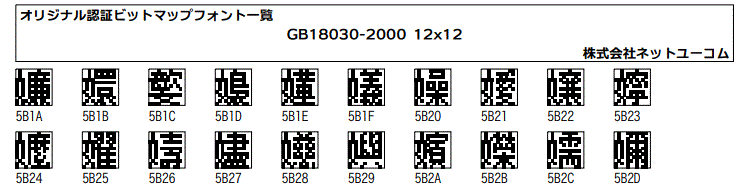
認証フォントをご理解いただいている方には「オリジナル認証フォント」のご提案をさせていただきます。当社保有のGBフォント(中国語ビットマップフォント)は、日本で初めてNIPCの認証を受けたメーカであり、その技術を応用し100%コンパチなGBフォントを制作、民間企業の試験を受けGB規格の中国認証ビットマップフォント(NIPC)と差異の無いことを確認しました。
ネットユーコムの「オリジナル認証フォント」はGB/T11460-2000の規定によりネイティブ認証フォントと全く同じ字形です。ビットマップフォントは制作に多くの時間が必要で制作コストがかかります。それゆえに多くのフォントベンダーでは数千USドルから数万USドルと高価です。当社は多くのお客様へご提供することで回収できると考え一定数を超えると判断できる製品については格安にて開放します。当社よりご提供する中国語簡体字ビットマップフォントは全てGB規格に合致した製品です。
「文字セットGB2312」は、GB2312コードに準拠した文字セットです。
認証など検査は行われおりませんが、GB規格のコードには合致しており認証フォントの水準に達しております。日本国内及び中国を除く海外向けに広く実績があります。測定器や機器搭載フォントとして十分な品質を備えております。
中易中標製品によるNIPC検査証付き
中国認証フォントと同じ字形デザインのGB規格書体
文字セット(コード体系)はGB2312ですが認証などは受けていない書体
2017年3月23日に強制国家標準(GB)が見直され推奨性国家標準(GB/T)への変更が263件実施されました。この中にはGB2312が含まれました。
GB/Tは「中華人民共和国 勧奨国家標準」勧奨ではありますが強制ではありません。この事で利用条件が緩和されたことになりなす。
一般に言われているGB2312の「認証」の必要性もございません。
お客様におかれましては、選択肢として従来の認証フォントをそのままご利用になる場合の他、新規に安価な同等品と差し替えることで開発費を抑えることが可能となりました。
※ GB認証済みフォントと100%同等です。
ドット位置を正確にプリントしたGB18030-2000簡体字一覧表
対応品 ボディサイズ (レターサイズ) 簡体字GB18030-2000相当 28,521文字
掲載する文字一覧は株式会社ネットユーコムが保有販売するオリジナル認証フォント製品のうち、1)~4) サイズのGB18030-2000相当全文字をリアルにプリントしたものです。文字を表す字形のドットは、そのボディに対し正確にドット位置を示しています。同じ文字であっても製品サイズによってドット位置が異なります。正確な字形デザインを把握する場合は、該当サイズの文字コード表をご利用ください。当該製品はGB規格に基づき国家中文信息处理产品质量监督检验中心(NIPC) に検査合格した認証フォントを元に作成したオリジナル認証フォントのリアルな文字一覧です。